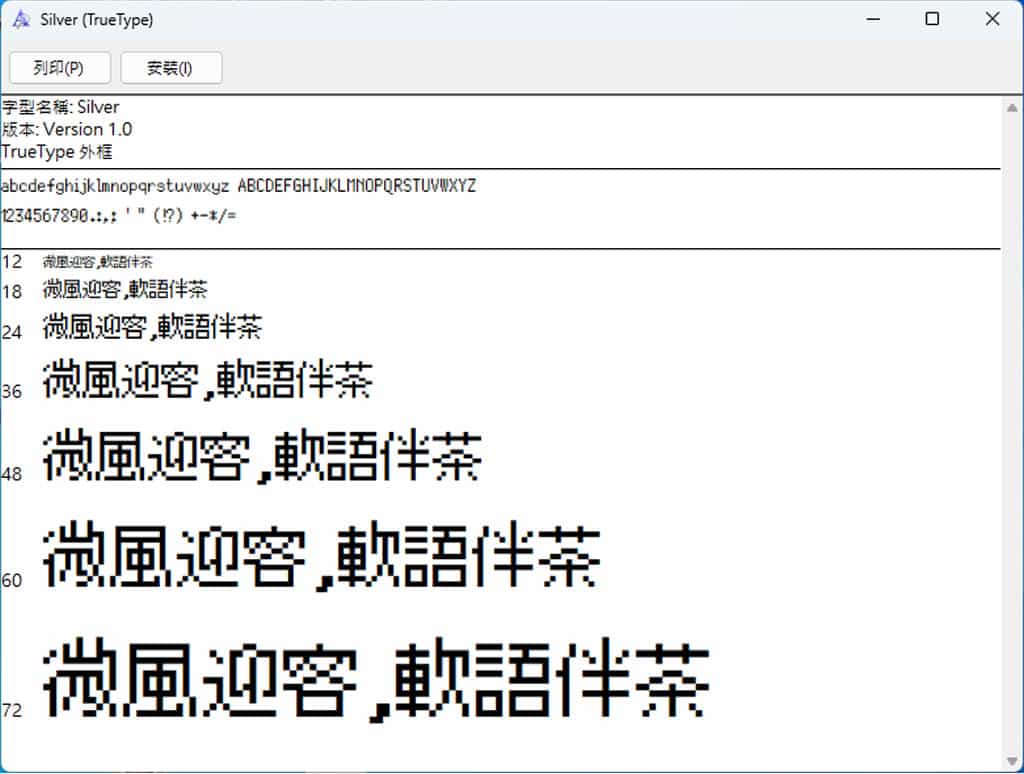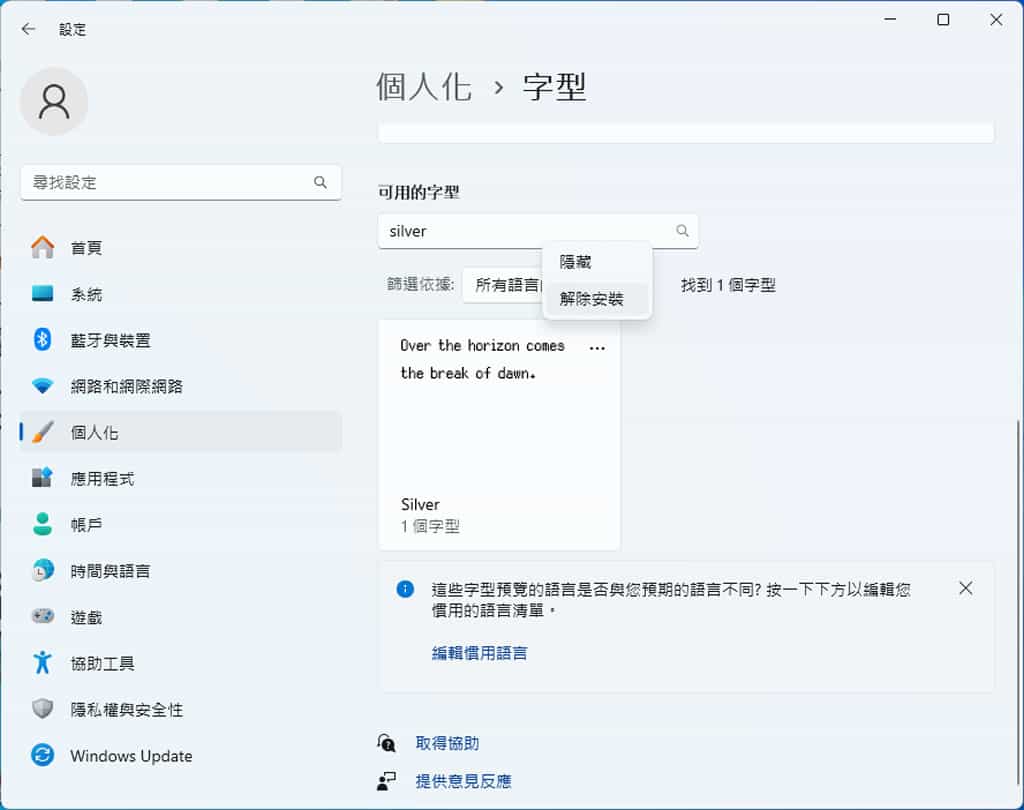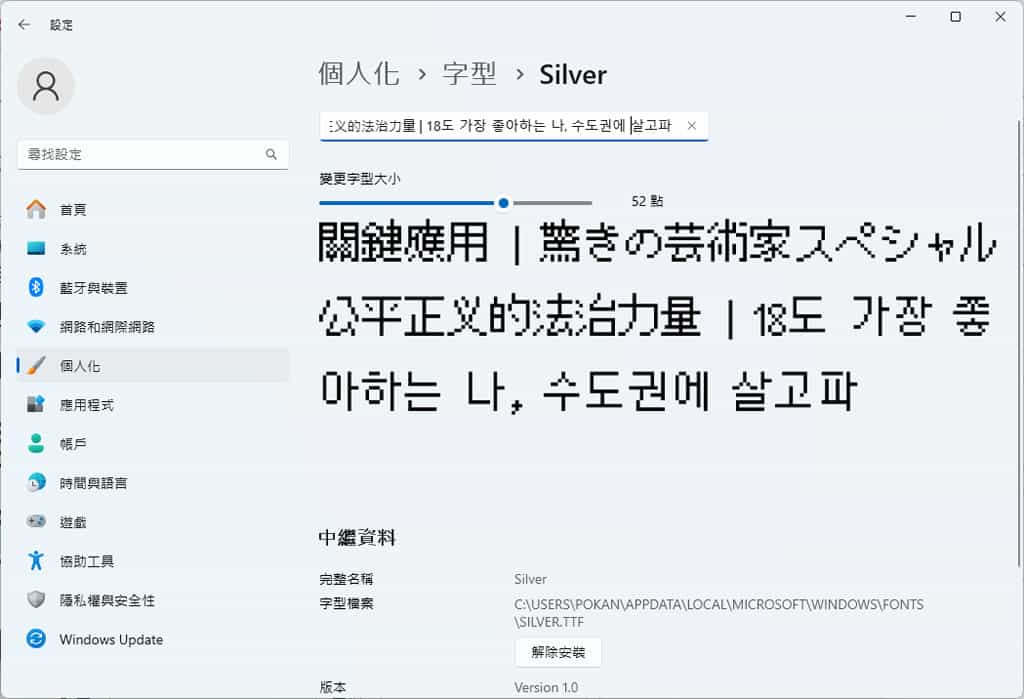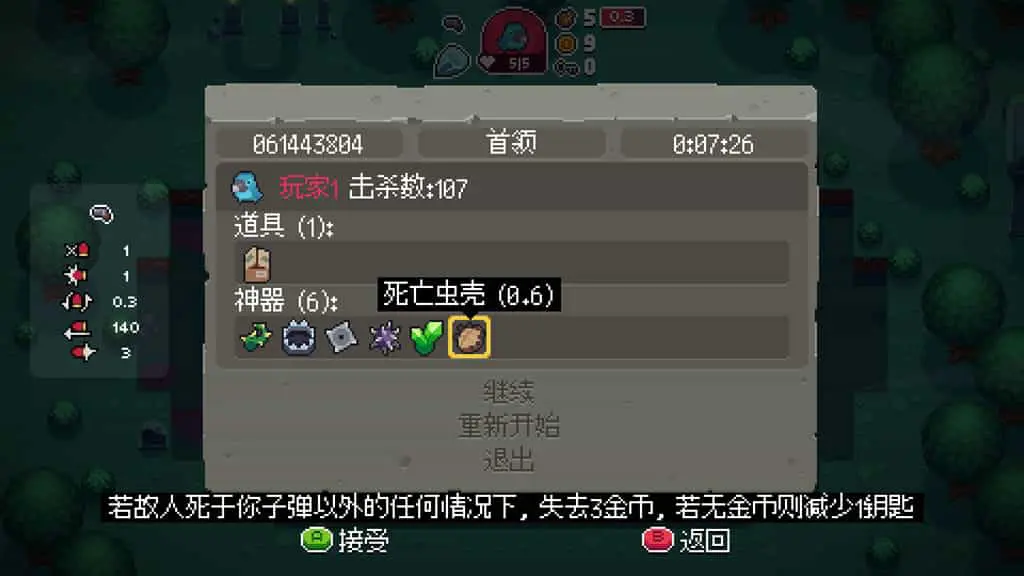
Silver 字型:支援簡、繁中文及多語言的像素字體,專為遊戲開發與設計打造
Silver 是一款專為遊戲開發者與像素風格愛好者設計的多語言像素字型。它支援英文、日文、韓文,以及簡繁體中文,確保各語系玩家都能無障礙體驗。此外,Silver 內建符合 TRC(Technical Requirements Checklist) 和 Lotcheck 標準的遊戲手把按鈕符號,並提供完整的鍵盤與滑鼠操作提示,使其成為像素遊戲 UI、復古海報設計的理想選擇。
為滿足不斷變化的遊戲與應用程式需求,Silver 字型仍持續更新,新增更多 Unicode 字元,確保其在各種遊戲與應用場景中的兼容性。該字型採用 CC BY 4.0 授權,可自由使用與修改,適合遊戲開發、像素風格設計、數位藝術等多種應用。
涵蓋中、英、日、韓語系,內建 TRC 與 Lotcheck 遊戲按鈕符號,適用於像素遊戲與復古設計